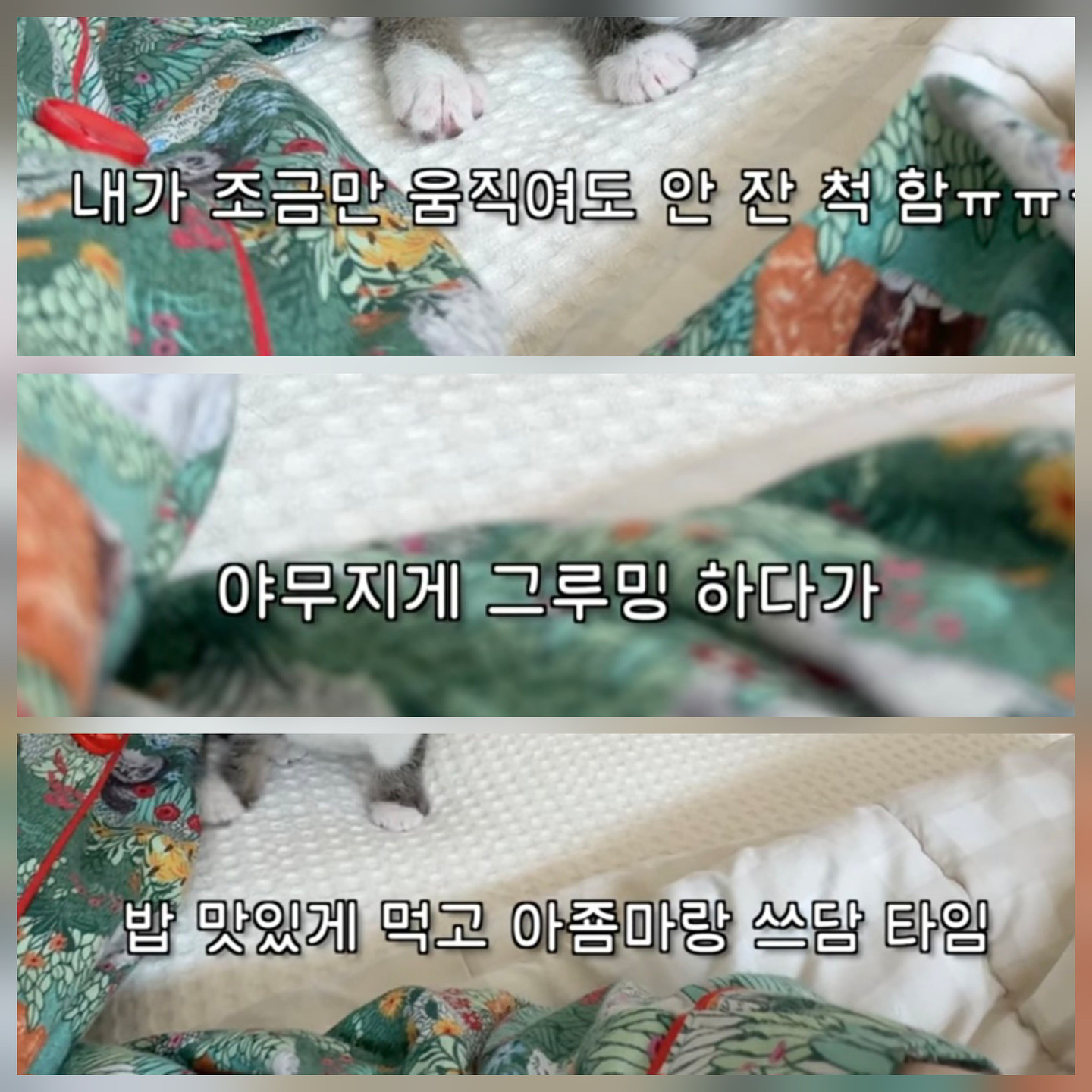
혹시 해당 굴림체 아시는 분 계실까요? 초중종성 획이 떨어져있고, ㅅ, ㅈ이 저렇게 대칭으로 생겼습니다 ('잔', '척'을 보면 마지막 획이 좀 짧습니다) ㄱ, ㄹ, ㅌ이 초성일때 끝이 좀 굴려져있고 ㅇ, ㅁ, ㅂ이 너비를 꽉채우는 비율로 쓰이는데 사이즈가 작게쓰입니다 ㅎ의 모자도 저렇게 작게 떨어져있습니다. 아시는 폰트라면 부디 답변주시면 감사드리겠습니다..!ㅠㅠ